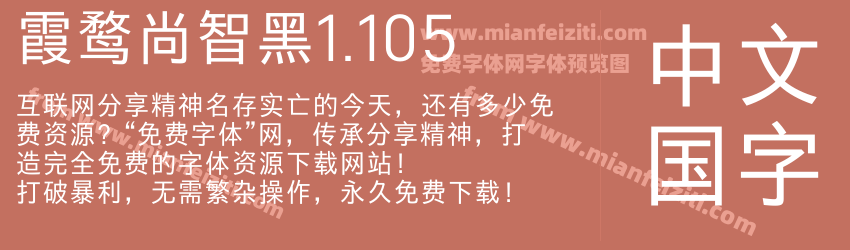
霞鹜尚智黑1.105
字体名称: 霞鹜尚智黑1.105
Postscript名称: LXGWFasmartGothic
霞鹜尚智黑,在「03スマートフォントUI」的基础上修改制作,将新晰黑字面横向压缩 94%,全新英数与假名,更具稳重时尚感。(注:尚智黑的符号相比于新晰黑会有所欠缺,且可能在后续更新中随时撤消,敬请留意。)
本款“霞鹜尚智黑1.105”是一款书写很新颖的字体,字体大方,适合各种设计作品使用!欢迎下载!